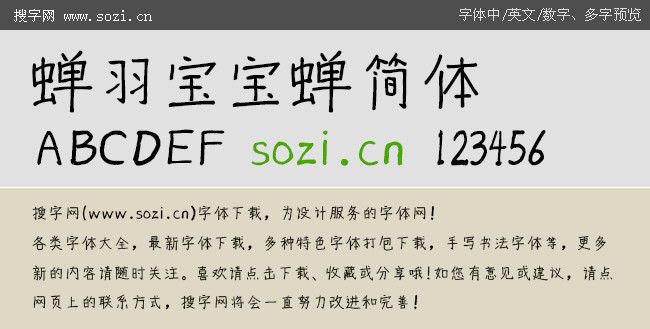
蟬羽寶寶蟬簡體
搜字網(wǎng)提供一款蟬羽寶寶蟬簡體中文字體下載,蟬羽寶寶蟬簡體是一款個(gè)性手寫字體,字形樸實(shí)無華,自然天成,筆畫細(xì)膩,整體連貫,部分字體帶著微小的差距,整體上比較和諧,能夠適用于藝術(shù)設(shè)計(jì)、包裝印刷、簽名設(shè)計(jì)、圖形設(shè)計(jì)等領(lǐng)域。(本字庫版權(quán)歸王建剛個(gè)人所有,商用需經(jīng)作者許可)